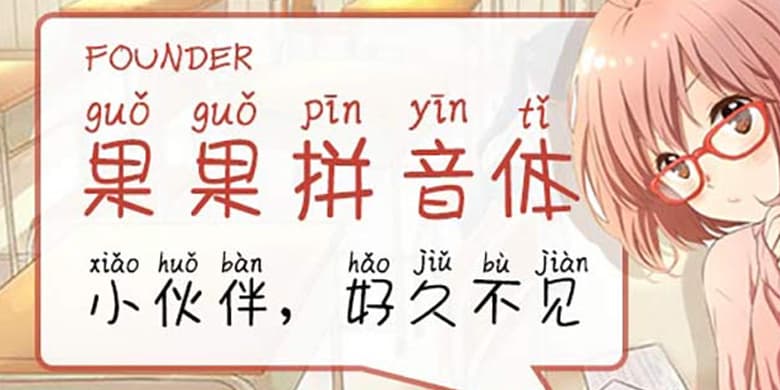
方正手迹-果果拼音体
品牌:方正手迹设计师:龙顺福发行时间:2020字库编码:大陆简体(GB2312-80)分类:创意书写字体属性:精品字
果果拼音体这是一款卡通风格的拼音体,字身线条主要由斜线和大角度的弧线构成,简单的同时最大限度的增加了字面,使字体简洁易读,展示效果极佳。口、日、田等封闭空间的处理独具特色,都是由两段对称的弧形拼接而成,动感十足,节奏感强烈。适用于少儿类的书刊、品牌广告和产品包装设计,综艺漫画用字,以及社交网络的个性化用字。